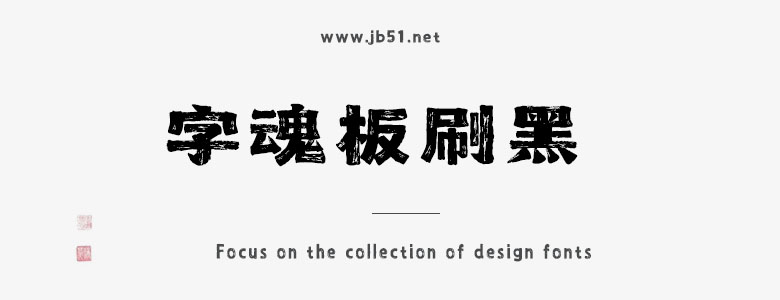
字魂板刷黑字體是由字魂字庫推出的毛筆書法字體,這款字體包含9500個(gè)中文、字母、 符號(hào)和數(shù)字,具有中國風(fēng)的風(fēng)格,適合應(yīng)用于藝術(shù)設(shè)計(jì)、平面宣傳設(shè)計(jì)、網(wǎng)頁設(shè)計(jì),書法字帖等領(lǐng)域。
字魂板刷黑字體是一款商用的硬筆手寫,毛筆書法,創(chuàng)意字體,該字體包含7144個(gè)中文、字母、 符號(hào)和數(shù)字,具有中國風(fēng)的風(fēng)格,可以滿足您設(shè)計(jì)上的各種需求,該字體主要用于標(biāo)題字等場景, 您不但可以在字魂網(wǎng)下載字魂板刷黑字體,同時(shí)還有眾多毛筆書法字體、創(chuàng)意字體等可供選擇!